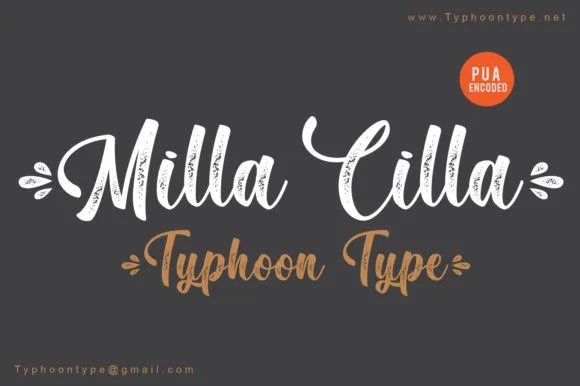
A fonte Milla Cilla Script é uma introdução ao mundo naturalmente desenhado do tipo de letra, cheio de fios delicados que se movem e se curvam como um script real. Desenvolvida pelo designer Typhoon Type – Suthi Srisopha, ela traz uma sensação de luxo e sofisticação para qualquer projeto de design. Perfeita para adicioná-la ao seu trabalho, este tipo de letra oferece o que há de melhor em recursos de script – um rastro elegante e um toque refinado. Com PUA encodado, você pode facilmente acessar todos os belos caracteres e ligaturas disponíveis. Seja para dar aquele toque extra a sua página web ou impressão, esta fonte Milla Cilla Script é uma escolha inteligente que irá chamar atenção. Com um design natural e fluido que se move como uma escrita real, você pode explorar o mundo de tipos de letras criados pelo designer Typhoon Type – Suthi Srisopha. Este tipo de letra está repleto de vida e estilo, trazendo a sofisticação do script em seu próprio ritmo.